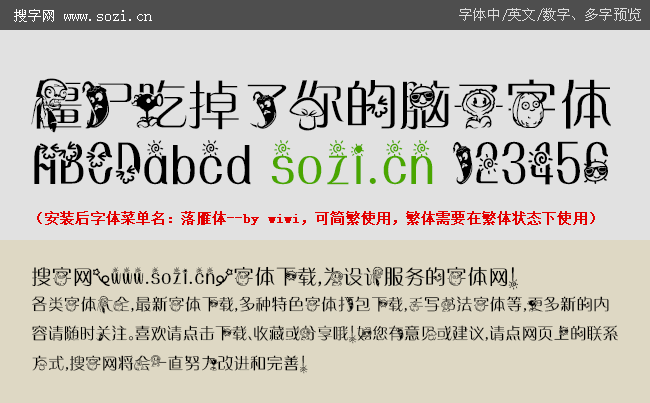
僵尸吃掉了你的腦子字體
搜字網(wǎng)給大家提供一款很有趣的手機(jī)中文字體下載。在這個(gè)張揚(yáng)個(gè)性的時(shí)代里,沒有一個(gè)個(gè)性的手機(jī)字體腫么能行,這款手機(jī)字體是在倩體上進(jìn)行修改,筆畫間插入了有趣的植物大戰(zhàn)僵尸游戲卡通圖案。真是趣味性實(shí)足的一款手機(jī)字體,該中文字體個(gè)性實(shí)足,趣味性強(qiáng),又保持了文字的識(shí)別度,特別適合喜歡植物大戰(zhàn)僵尸游戲又想手機(jī)字體個(gè)性一些的朋友在手機(jī)上安裝使用。